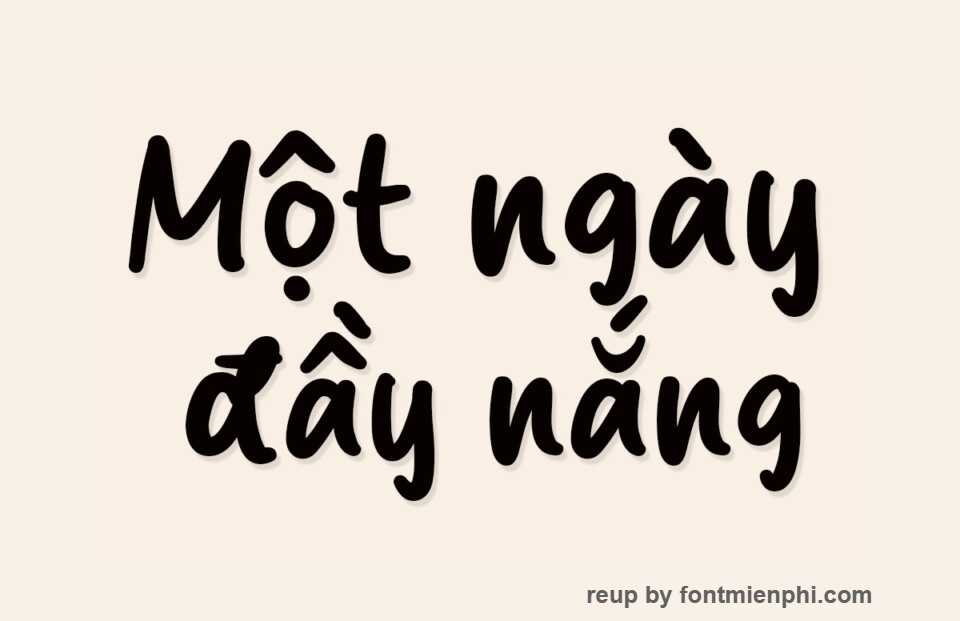
Font Việt hóa 1FTV VIP Believe Script
Trong thế giới thiết kế đồ họa hiện đại, phông chữ không chỉ đơn thuần là công cụ truyền tải thông điệp bằng văn bản mà còn là “linh hồn” tạo nên cảm xúc, thần thái và giá trị thương hiệu cho mỗi sản phẩm. Nếu bạn đang tìm kiếm một nét chữ mềm mại, quyến rũ nhưng vẫn giữ được vẻ sang trọng và đẳng cấp, Font Việt hóa 1FTV VIP Believe Script chính là giải pháp hoàn hảo dành cho bạn. Được Việt hóa tỉ mỉ đến từng chi tiết, bộ font này đáp ứng trọn vẹn nhu cầu sáng tạo của các nhà thiết kế đồ họa, blogger, cho đến các đơn vị truyền thông chuyên nghiệp tại Việt Nam.
Font Việt Hóa 1FTV VIP Believe Script – Đỉnh Cao Nghệ Thuật Calligraphy Dành Cho Thiết Kế Sang Trọng
Font Việt hóa 1FTV VIP Believe Script là một tác phẩm nghệ thuật chữ nổi bật thuộc dòng uốn lượn (Script/Calligraphy), được thiết kế nhằm mang lại vẻ đẹp tự nhiên như nét chữ viết tay tinh tế của một nghệ nhân. Điểm đặc trưng của bộ font này nằm ở sự kết hợp mượt mà giữa các đường nét thanh đậm nhịp nhàng, các nét uốn cong bay bổng và cấu trúc chữ vô cùng vững chắc. Việc được Việt hóa chuẩn xác giúp phông chữ loại bỏ hoàn toàn hiện lỗi font hay sai lệch khoảng cách dấu khi nhập tiếng Việt – sự cố vốn rất phổ biến ở các bộ font quốc tế chưa qua xử lý.
Không chỉ dừng lại ở sự thẩm mỹ, 1FTV VIP Believe Script còn được tối ưu hóa đặc biệt dành cho các nhà thiết kế Việt Nam. Bộ dấu tiếng Việt được tạo hình khéo léo để không làm mất đi tính cân đối của tổng thể ký tự, giữ cho các nét uốn swash không bị đè lên dấu thanh hay làm rối mắt người xem. Dù được sử dụng trên các ấn phẩm in ấn cao cấp hay trong các chiến dịch truyền thông kỹ thuật số, bộ font này vẫn luôn toát lên vẻ thu hút khó cưỡng, giúp tác phẩm thiết kế của bạn dễ dàng nổi bật giữa đám đông.
1. Hỗ Trợ Tiếng Việt Chuẩn Xác Với Hệ Thống Dấu Được Tối Ưu Tỉ Mỉ
Một trong những thách thức lớn nhất khi sử dụng các phông chữ Script quốc tế là vấn đề lỗi hiển thị tiếng Việt. Với Font Việt hóa 1FTV VIP Believe Script, toàn bộ hệ thống ký tự tiếng Việt (bao gồm cả chữ hoa và chữ thường cùng hệ thống dấu thanh như sắc, huyền, hỏi, ngã, nặng và các dấu phụ như mũ, móc) đã được thiết kế lại hoàn chỉnh. Vị trí các dấu được đặt chuẩn xác về mặt thị giác, đảm bảo tính cân bằng giữa tính nghệ thuật của nét chữ uốn lượn và tính dễ đọc của văn bản. Bạn có thể thoải mái sáng tạo các câu slogan, câu quotes hay tiêu đề tiếng Việt mà không cần phải tốn thời gian chỉnh sửa dấu thủ công.</p>
2. Hệ Thống Ký Tự Thay Thế (OpenType Alternates) Và Swash Bay Bổng
Font 1FTV VIP Believe Script sở hữu một kho tàng ký tự thay thế (Alternate Characters) và nét gạch trang trí (Swashes) cực kỳ phong phú. Nhờ tính năng OpenType tiên tiến, người dùng có thể dễ dàng biến hóa các chữ cái đầu câu hoặc cuối câu thành những đường uốn lượn hoa mỹ, tạo điểm nhấn đầy nghệ thuật cho tác phẩm. Sự đa dạng của các nét nối (Ligatures) giúp các chữ cái liên kết với nhau một cách tự nhiên như dòng chảy của mực, mang lại cảm giác chân thực và mềm mại tuyệt đối cho từng dòng chữ.
3. Tính Ứng Dụng Đa Năng Cho Nhiều Loại Hình Thiết Kế Khác Nhau
Nhờ vẻ đẹp thanh lịch và kiêu sa, 1FTV VIP Believe Script là sự lựa chọn ưu tiên hàng đầu cho nhiều mảng thiết kế sáng tạo. Bộ font này đặc biệt phù hợp cho các dự án đòi hỏi tính thẩm mỹ cao như:
• Thiết kế thiệp cưới và sự kiện: Tạo nên những bộ thiệp cưới lãng mạn, sang trọng, mang lại ấn tượng sâu sắc cho khách mời.
• Nhận diện thương hiệu (Branding & Logo): Hoàn hảo cho các thương hiệu thời trang, spa, mỹ phẩm, trang sức hoặc các sản phẩm cao cấp muốn thể hiện sự tinh tế.
• Bao bì sản phẩm: Nâng tầm giá trị thị giác cho hộp quà, chai nước hoa, nhãn rượu hay bánh kẹo cao cấp.
• Ấn phẩm truyền thông & Social Media: Tạo các hình ảnh trích dẫn (quotes), banner quảng cáo, bìa sách hoặc poster sự kiện thu hút lượt tương tác cao.
5. Đường Nét Vector Tối Ưu Hóa Cho Chất Lượng Hiển Thị Và In Ấn Sắc Nét
Mỗi ký tự trong bộ font 1FTV VIP Believe Script đều được vẽ và làm sạch đường nét (node) một cách chuẩn xác. Điều này giúp font chữ duy trì sự mượt mà tuyệt đối ngay cả khi bạn phóng to để in trên các bảng hiệu khổ lớn, backdrop sân khấu hay khi thu nhỏ trên màn hình điện thoại di động. Hiện tượng răng cưa hoặc méo nét hoàn toàn không xảy ra, giúp các nhà in ấn và thiết kế tiết kiệm thời gian xử lý tệp tin và cam kết chất lượng đầu ra tốt nhất cho khách hàng.
Ứng Dụng Thực Tế Của Font 1FTV VIP Believe Script Trong Dự Án Sáng Tạo
Để khai thác tối đa vẻ đẹp của Font Việt hóa 1FTV VIP Believe Script, việc kết hợp phông chữ này với các phông chữ khác trong cùng một bản thiết kế đóng vai trò rất quan trọng. Nhờ tính chất mềm mại và mang tính trang trí cao, 1FTV VIP Believe Script hoạt động hiệu quả nhất khi được sử dụng làm phông chữ điểm nhấn (Display Font) cho các tiêu đề chính, tên thương hiệu hoặc các từ khóa quan trọng.
Font Việt hóa 1FTV VIP Believe Script chắc chắn là một mảnh ghép hoàn hảo còn thiếu trong bộ sưu tập của bất kỳ designer yêu thích phong cách chữ viết tay mềm mại và sang trọng. Với sự đầu tư kỹ lưỡng về mặt kỹ thuật Việt hóa, tính năng OpenType đa dạng cùng khả năng tương thích cao, bộ font này hứa hẹn sẽ mang đến luồng sinh khí mới cho các dự án thiết kế thiệp cưới, bao bì, logo và truyền thông của bạn.